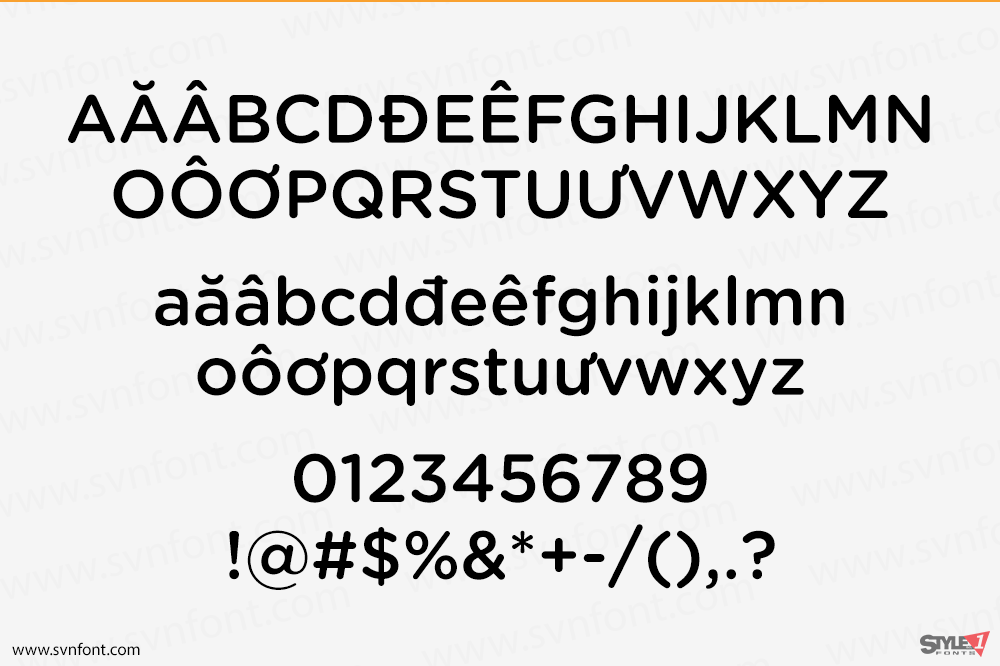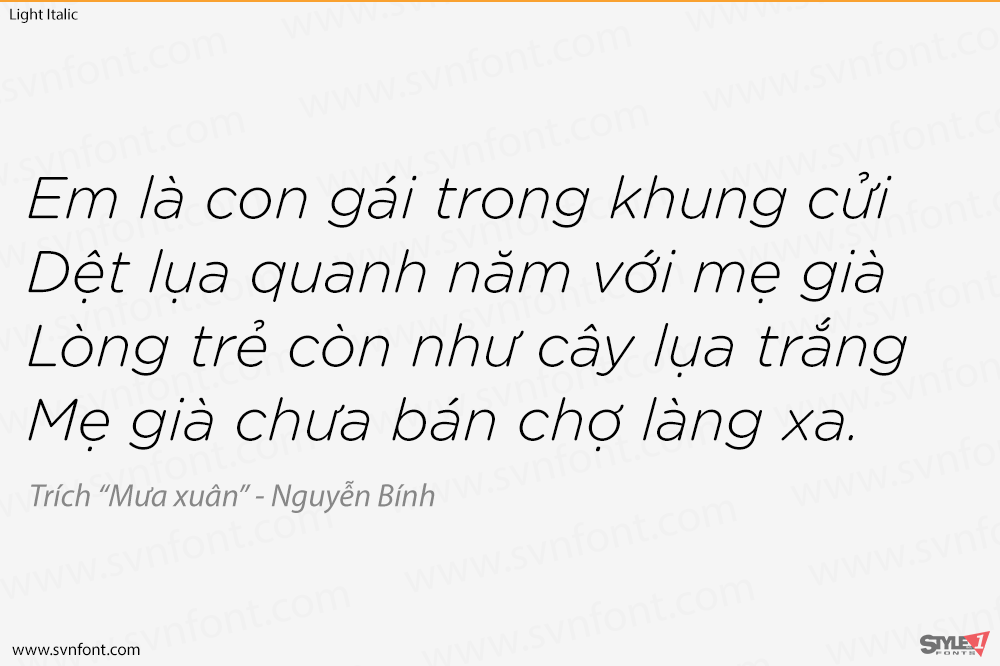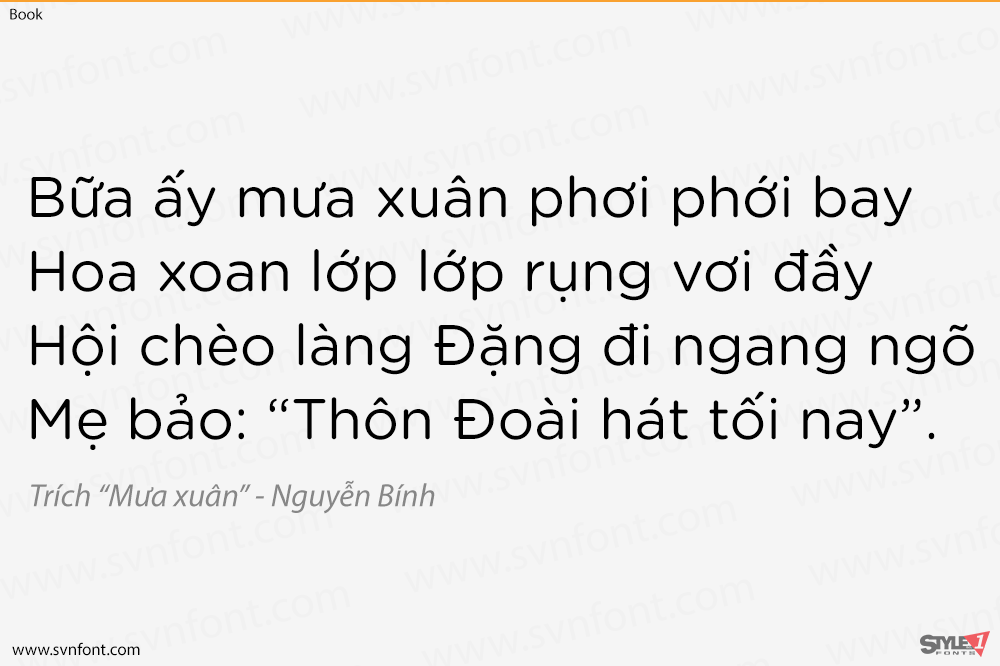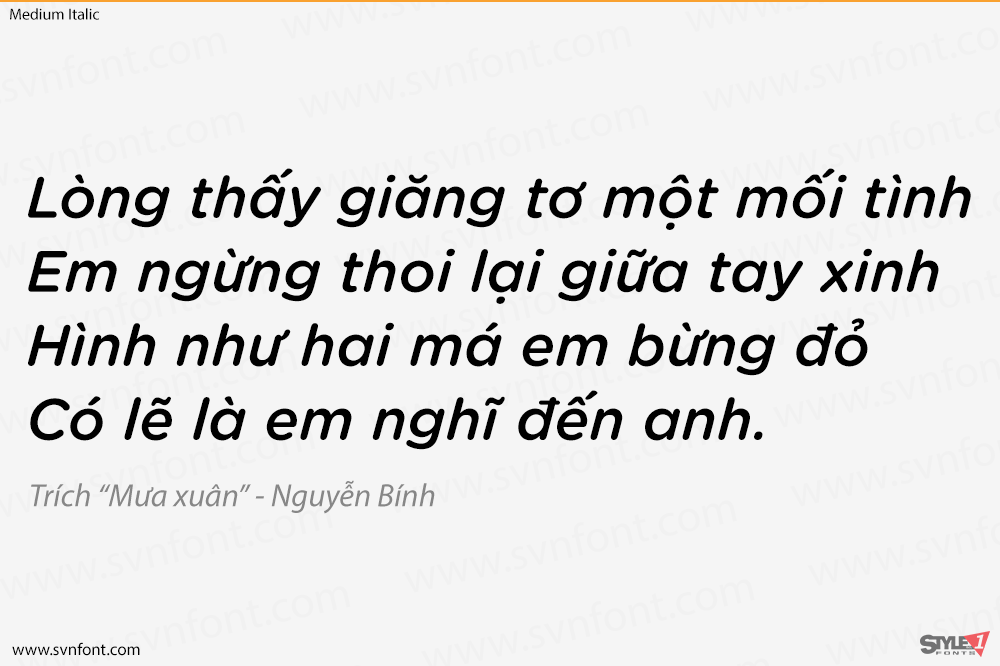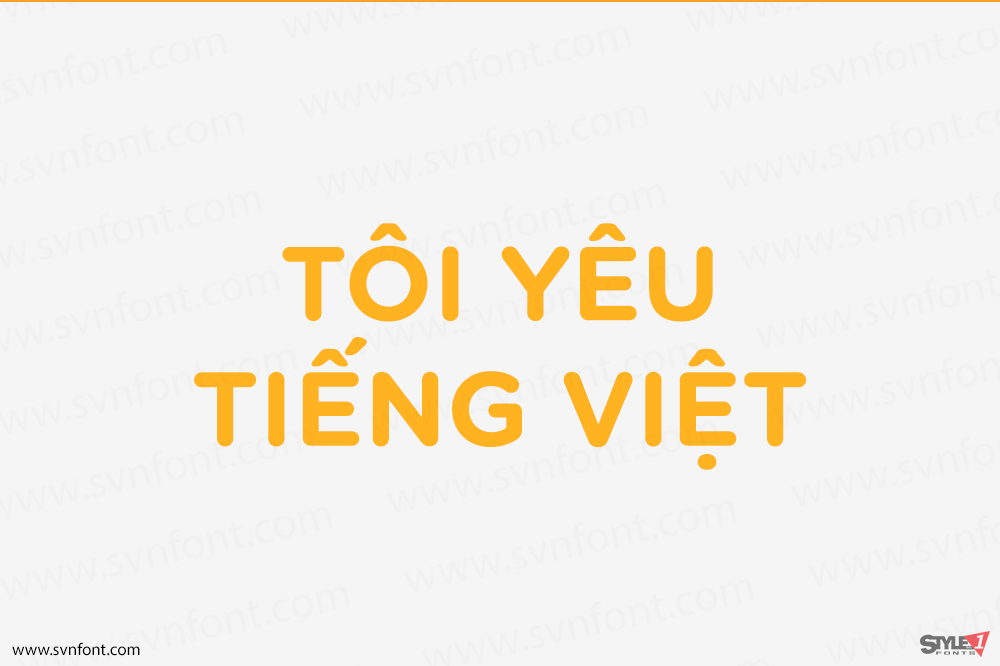
Gotham Rounded là một kiểu chữ kỹ thuật có thể dễ dàng biến hóa từ thân thiện đến công nghệ cao đến tinh nghịch. Kiểu chữ Gotham của chúng tôi, lấy cảm hứng từ các biển hiệu trên các tòa nhà, tôn vinh “bảng chữ cái của người thợ” ở quy mô hoành tráng.
Tương tự như vậy, nhưng ở kích thước gần gũi hơn, là kiểu chữ kỹ thuật: các dấu hiệu trên dụng cụ chính xác, bản thiết kế, khuôn mẫu và mẫu vẽ. Được vẽ, dập, khắc và cắt bằng máy, những hình thức này được nắm bắt một cách tinh tế bởi họ phông chữ Gotham Rounded mới của chúng tôi, có sẵn ở tám kiểu bao gồm cả kiểu in nghiêng.
Nhà thiết kế: Tobias Frere-Jones
Nhà phát hành: Hoefler & Frere-Jones